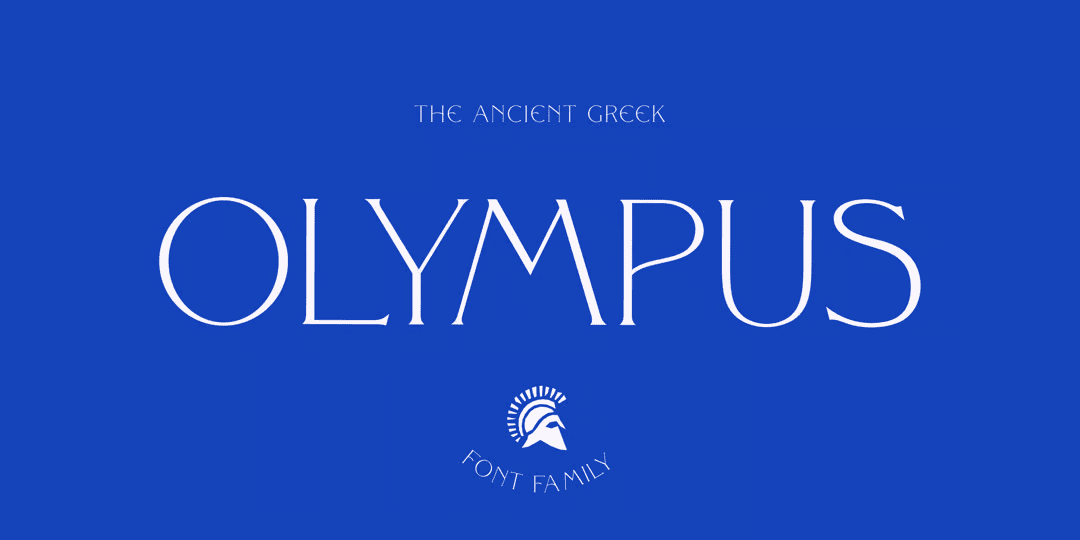
Olympus
やや手書き感の残るエレガントなディスプレイローマン。画像のスペルではあまり分からないが、他の字のグリフは割と曲線が多く、特に小文字は結構ふにゃふにゃしていて手書きのニュアンスが大きい。セリフは分かるか分からないかぐらいの小さなのがちょこんと付いている。細いウェイトはエレガントだが、太いものもあってそちらはこの雰囲気は失われる。まあ用途によって使い分けるといいだろう。名前は医療機器・カメラメーカーではなく、ギリシャ最高峰にしてギリシャ神話の神々が住まうとされるオリュンポス山のこと。当然ながらギリシャ文字もサポートしている。5ウェイト。